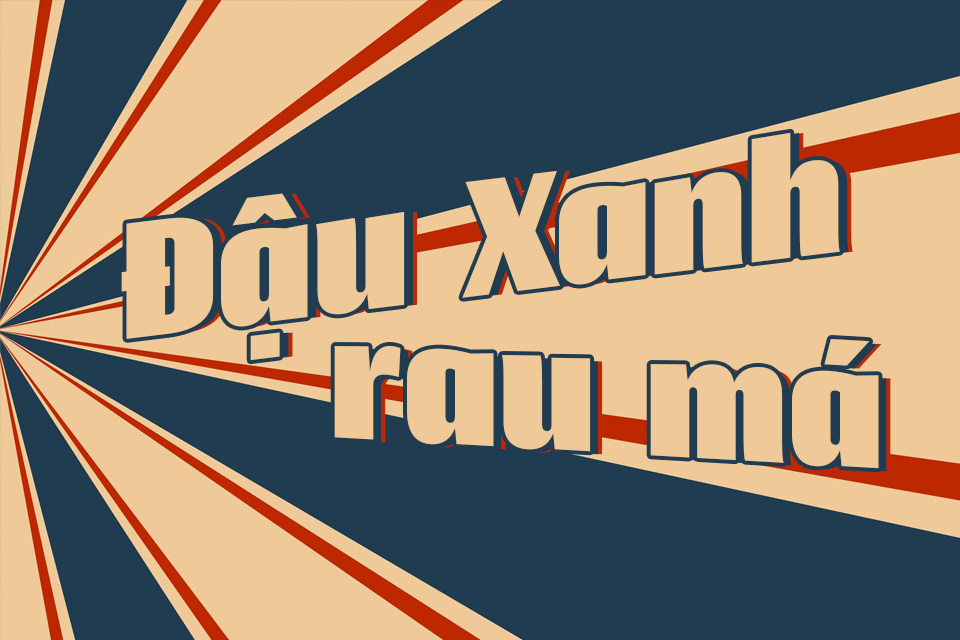
Giới thiệu về Font việt hoá MJ Grueso trong thiết kế đồ họa
Trong thế giới sáng tạo, việc lựa chọn một Font Chữ phù hợp đóng vai trò quyết định đến sự thành công của một tác phẩm nghệ thuật. Font việt hoá MJ Grueso là một bộ phông chữ thuộc phong cách display cực kỳ ấn tượng, nổi bật với các đường nét dày dặn, mạnh mẽ và đầy cá tính. Được tinh chỉnh để phù hợp hoàn toàn với bảng mã tiếng Việt, bộ font này giúp các nhà thiết kế tại Việt Nam dễ dàng truyền tải thông điệp mà không lo lỗi hiển thị. Với cấu trúc hình khối vững chãi, MJ Grueso mang đến cảm giác hiện đại, uy nghiêm nhưng vẫn giữ được sự tinh tế cần thiết cho các dự án chuyên nghiệp.
Đặc điểm nổi bật của Font việt hoá MJ Grueso
Phong cách thiết kế mạnh mẽ và hiện đại
Đặc trưng lớn nhất của Font việt hoá MJ Grueso chính là độ tương phản cao và các nét chữ bo tròn mềm mại nhưng dứt khoát. Điều này tạo nên sự cân bằng hoàn hảo giữa nét cổ điển và hơi thở đương đại. Phông chữ này rất phù hợp cho các tiêu đề lớn, banner quảng cáo, hay các poster phim đòi hỏi sự thu hút ngay từ cái nhìn đầu tiên. Ngoài ra, tính ứng dụng của nó còn mở rộng sang mảng thiết kế logo và nhận diện thương hiệu cho các doanh nghiệp trẻ, năng động.
Khả năng tương thích và trải nghiệm người dùng
MJ Grueso đã được tối ưu hóa kỹ lưỡng, đảm bảo hiển thị sắc nét trên cả màn hình kỹ thuật số lẫn các ấn phẩm in ấn. Nhờ quá trình việt hóa chỉn chu, các dấu thanh được đặt vị trí hợp lý, giúp văn bản trở nên dễ đọc và thẩm mỹ hơn. Đối với các bạn học sinh và giáo viên, việc sử dụng phông chữ này trong các bài thuyết trình hay tài liệu học tập sẽ giúp nội dung trở nên sinh động, bắt mắt và chuyên nghiệp hơn bao giờ hết.